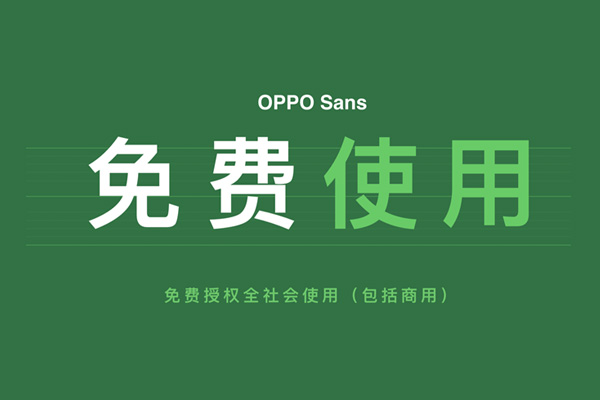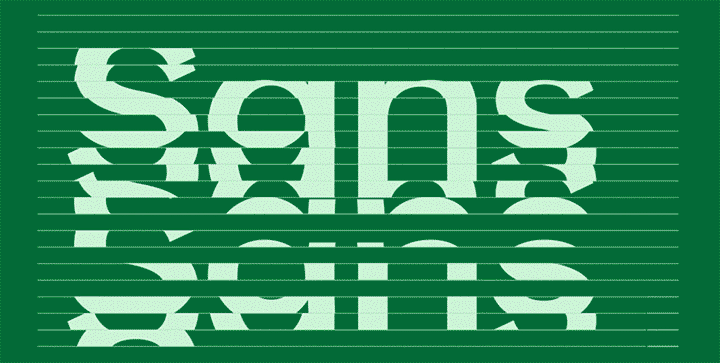
OPPO Sans 是 OPPO 公司推出的一款品牌定制无衬线字体,由汉仪字库与国际知名设计公司 Pentagram 联合打造,首发于 ColorOS 6 系统,2019 年在 ColorOS 7 发布会上正式宣布免费开放全社会使用(含商用)。
OPPO Sans 采用全新骨架,中宫自然舒适,结构稳定,字形舒展,强化了屏幕显示的易读性和外观性,简洁真实,体现了科技美感。提供五种常用字重,字符更是覆盖 21 国语言及 11 个语种,后续更新迭代还支持“无极字体”调节与自适应场景。不仅在移动端 UI、系统界面(ColorOS 原生适配)有很好的应用,也在科技、 数码类海报或宣传图、短视频封面、品牌手册等场景很常见。
- 2019 年:免费授权全社会使用(含商用),覆盖 21 国语言及 11 个语种,包含 Light、Regular、Medium、Bold、Heavy 五种字重。
- 2020 年:随 ColorOS 11 升级至 2.0 版本,支持“无极字体”调节与自适应场景。
- 2022 年:推出 3.0 版本,升级西文字体并调整中文字体匹配关系,获红点优胜设计奖。
- 2024 年:发布 4.0 版本,融合 Text 与 Display 字体特征,优化字母与数字设计,支持 OpenType 特性,新增 OPPO Serif 字体形成统一家族。